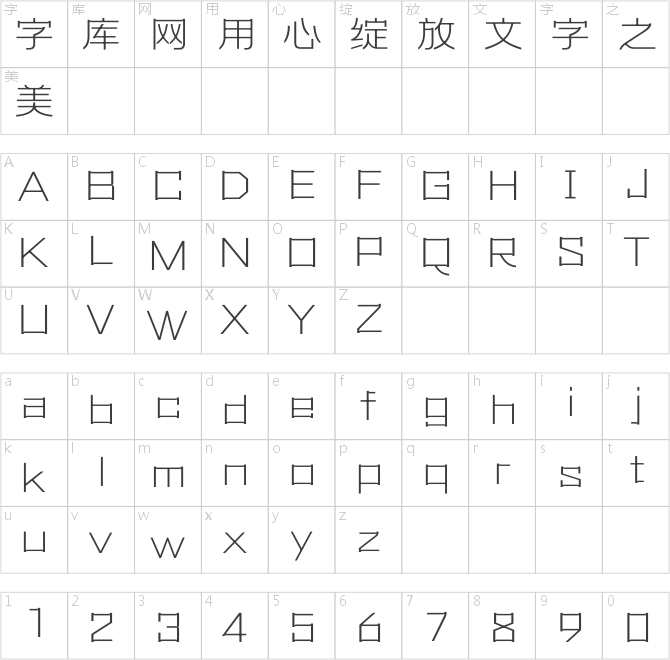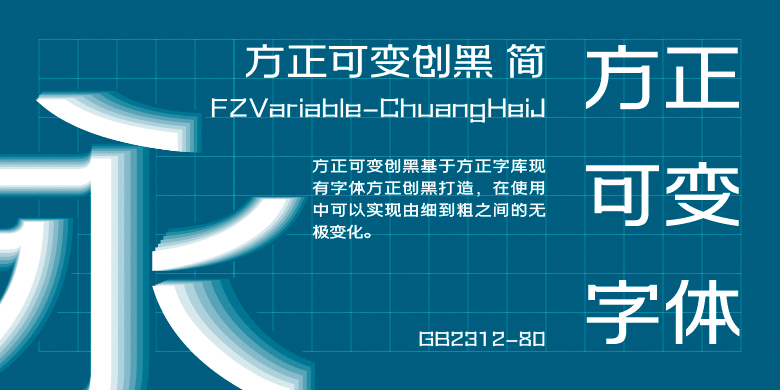
方正可變創(chuàng)黑 簡 詳情頁
方正可變創(chuàng)黑
方正可變創(chuàng)黑字體支持文字粗細(xì)無級調(diào)節(jié),設(shè)計師通過調(diào)整字重軸(Weight)的變化,可以實現(xiàn)字形的平滑連續(xù)的細(xì)微調(diào)整,滿足不同版式的設(shè)計需求。 創(chuàng)黑這款字的創(chuàng)意風(fēng)格來源于我們最常用的黑體字,在黑體的基礎(chǔ)上增強(qiáng)了字體結(jié)構(gòu)的飽滿度,加強(qiáng)了筆畫的韻律和節(jié)奏感,以及規(guī)范度讓整體字形更加簡潔易記同時兼?zhèn)渌囆g(shù)感。在橫豎筆畫轉(zhuǎn)角的處理上,加以傳統(tǒng)書法的提筆落筆,讓整體字形彰顯力量感頓挫感,在撇捺筆畫的走勢上,借鑒了宋體字筆畫的柔和度,讓整體字形摒棄黑體字的生硬,讓它更具優(yōu)雅性, 在創(chuàng)作過程中,我們始終讓字形兼具力量與優(yōu)雅并存,從而在簡潔的字形中,形成自身最大的特征。適用于產(chǎn)品包裝、海報視頻、大標(biāo)題及周邊等領(lǐng)域。